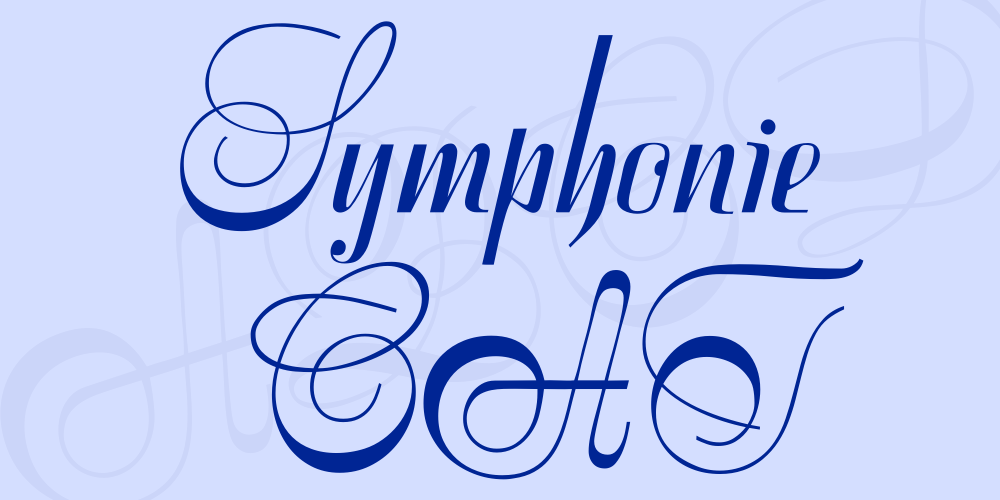
A Symphonie CAT é uma elegante fonte script criada pelo designer Peter Wiegel. Esta fonte traz uma sensação natural e envolvente que se adequa perfeitamente para aplicativos de design gráfico, como banners, logos ou trabalhos digitais. Com seu charme fluido e harmonioso, a Symphonie CAT é ideal para criar mensagens memoráveis em qualquer plataforma digital ou impressão. Ainda desconhecida por muitos, Peter Wiegel tem uma vasta gama de habilidades no design visual. Sua fonte é gratuita, o que torna ela um recurso valioso para designers e criadores de conteúdo iniciantes. Para aqueles interessados em explorar mais sobre Symphonie CAT, a página da web oficial do designer, www.peter-wiegel.de, oferece uma grande variedade de detalhes e informações úteis. Seja você um estudante de design ou um profissional experiente, a Symphonie CAT é certamente uma fonte que merece ser explorada.